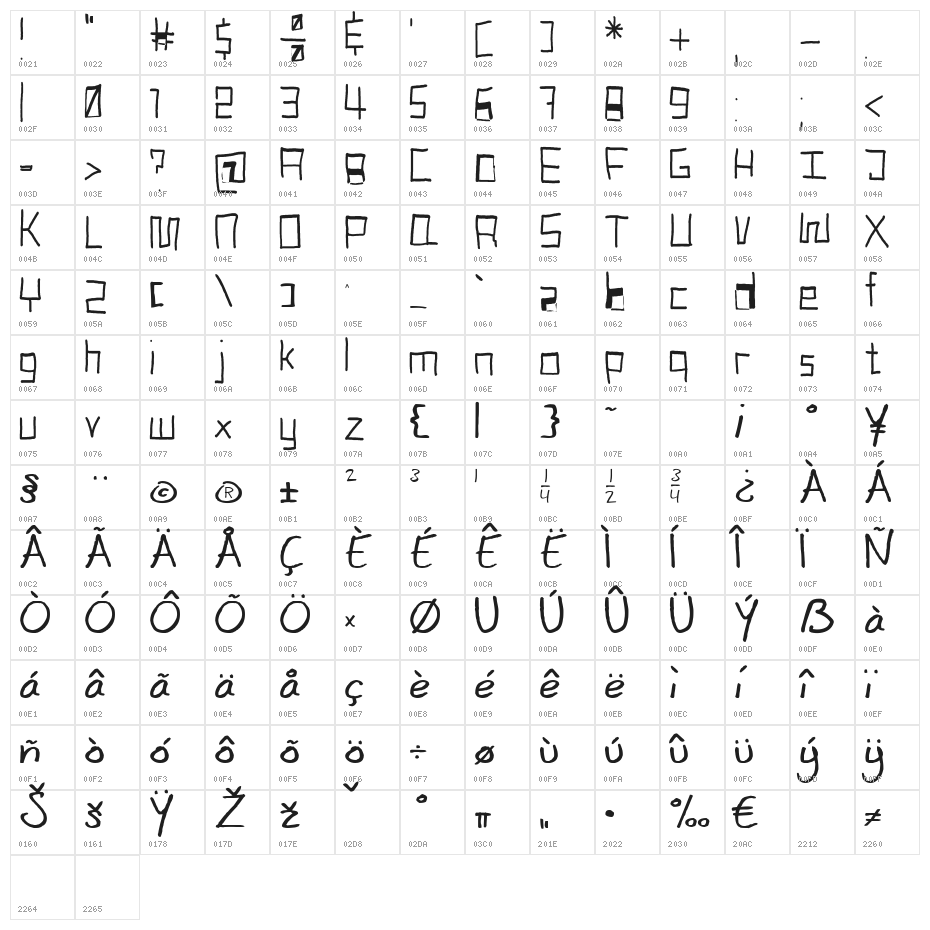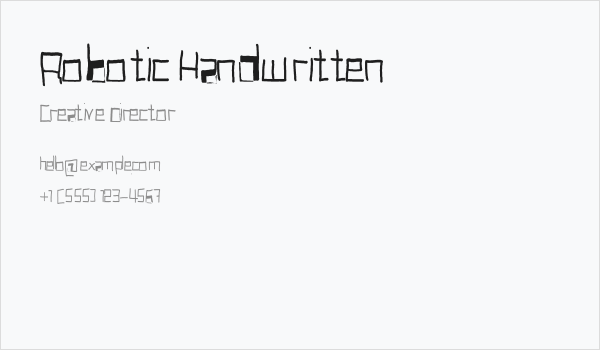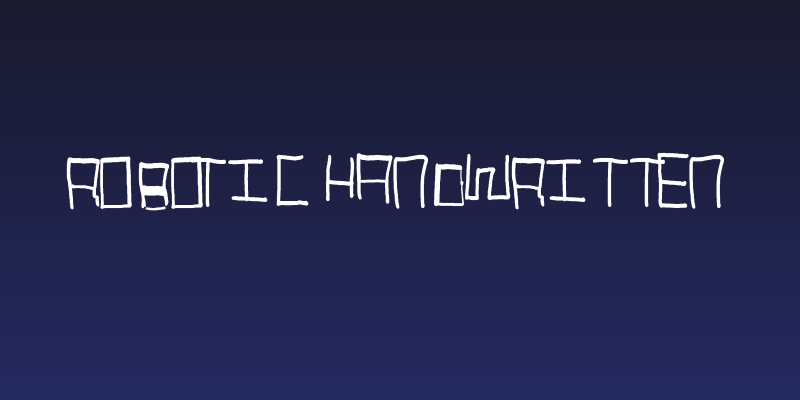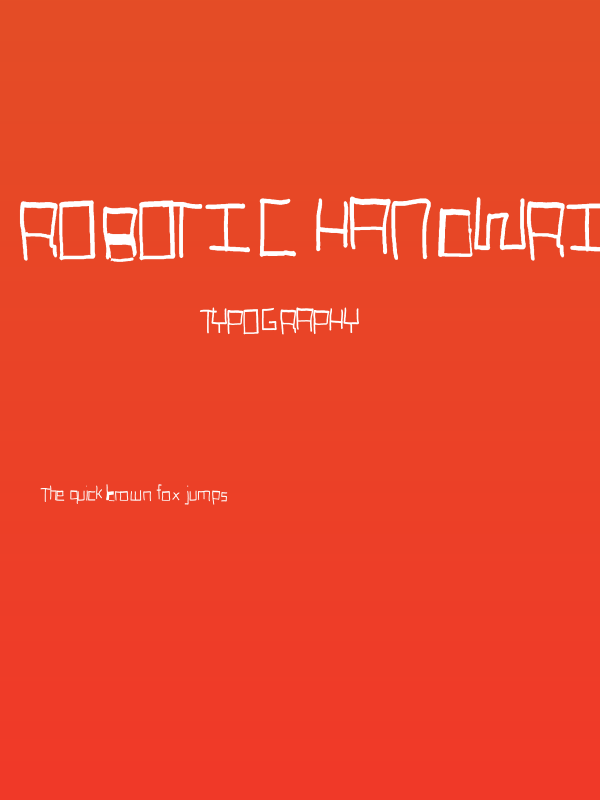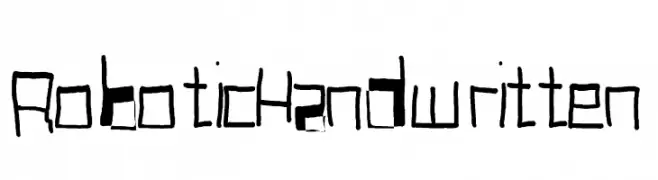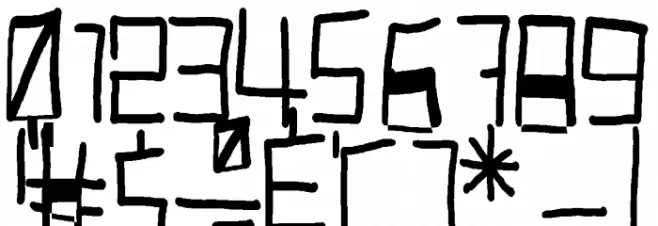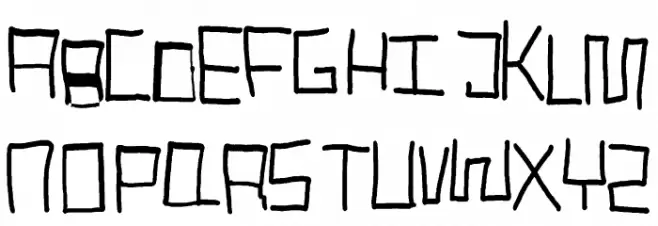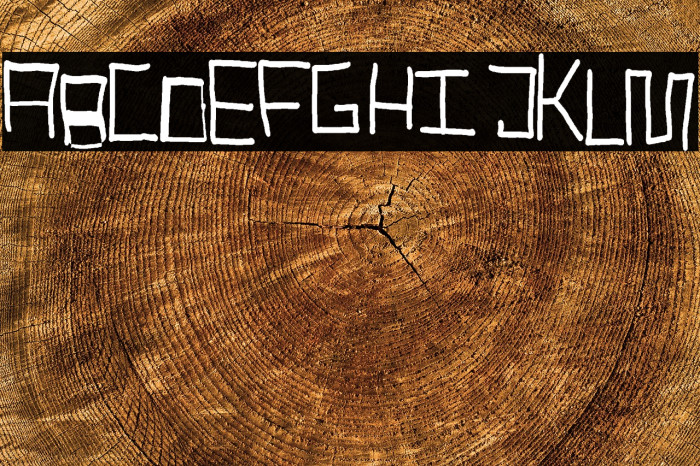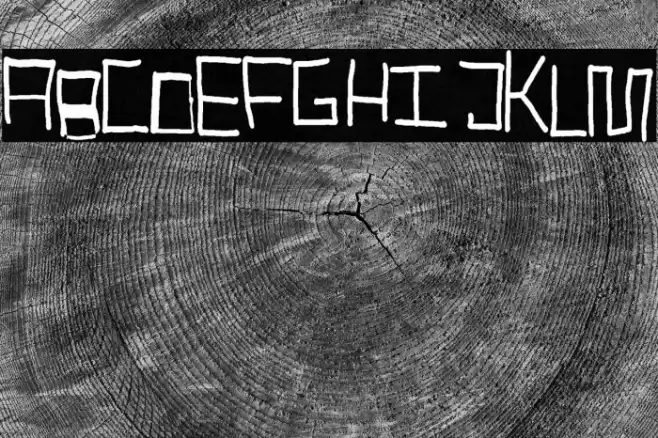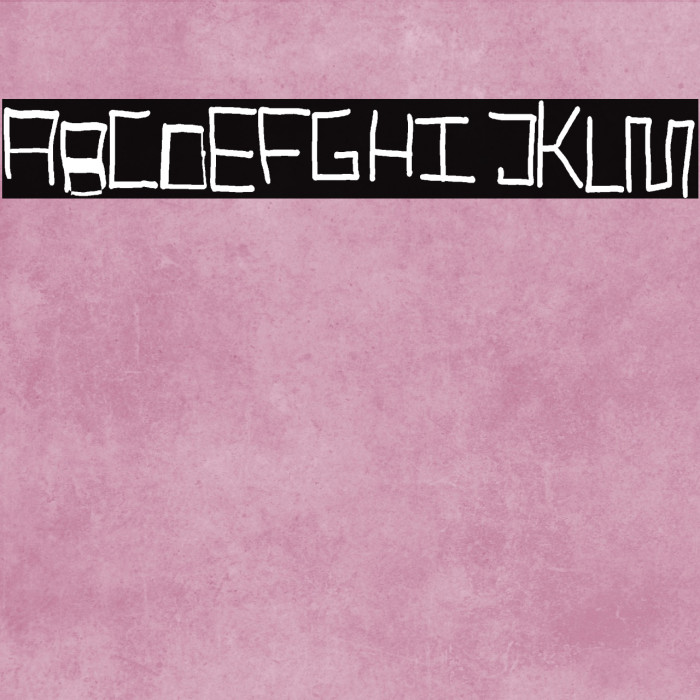
Robotic Handwritten Font
| Proyectos propuestos | Ideal for tech-themed posters, modern art projects, digital interfaces, and branding that seeks a personal yet futuristic touch. |